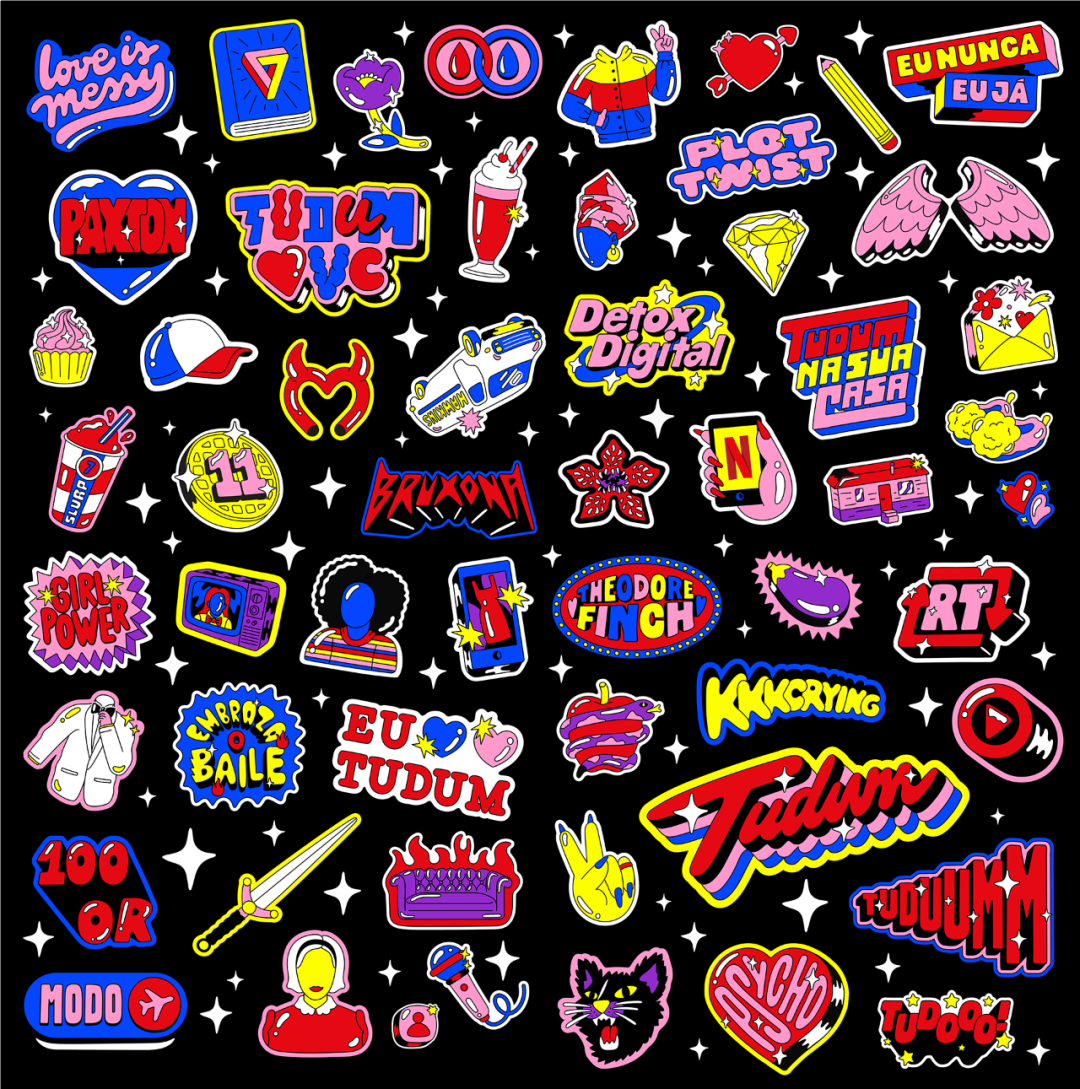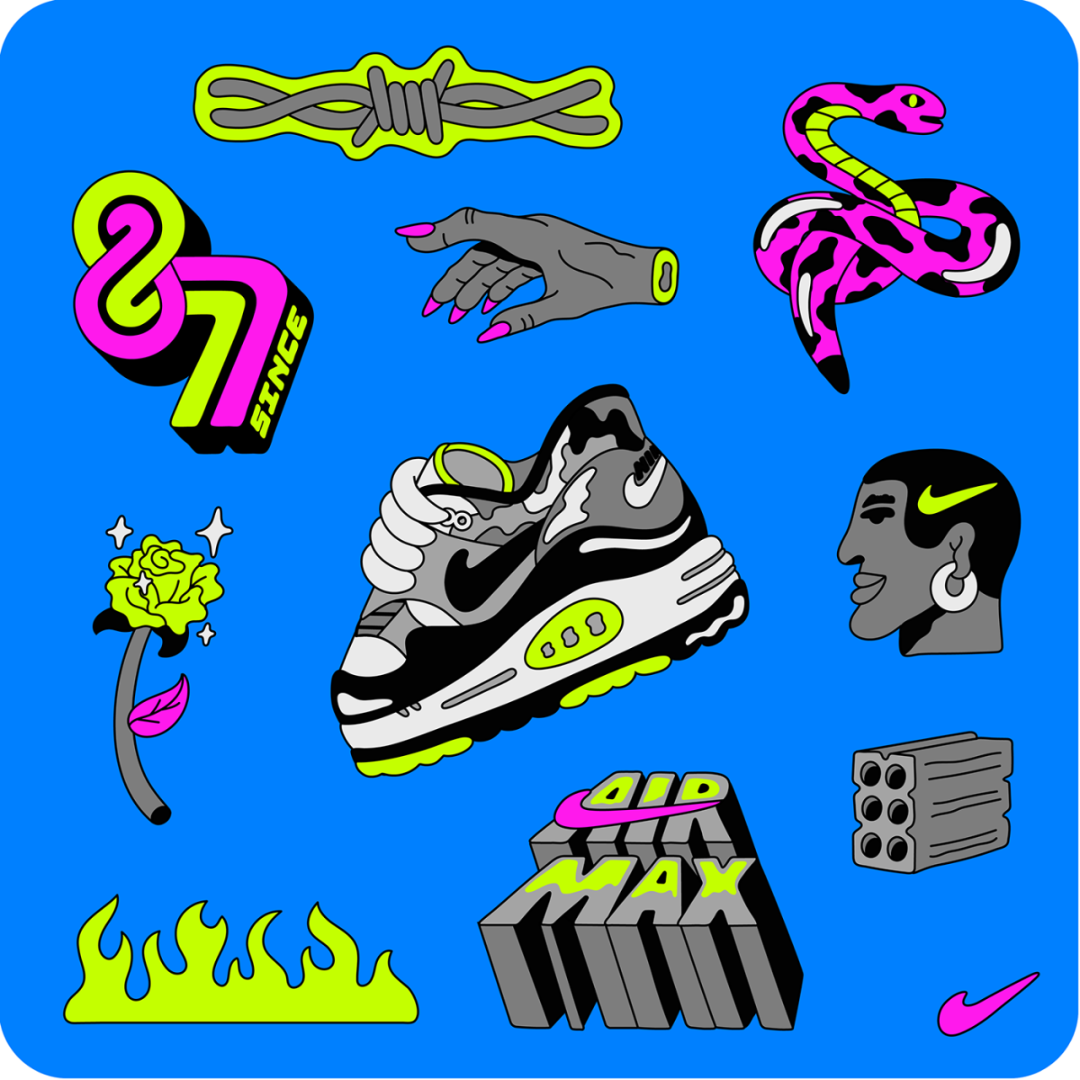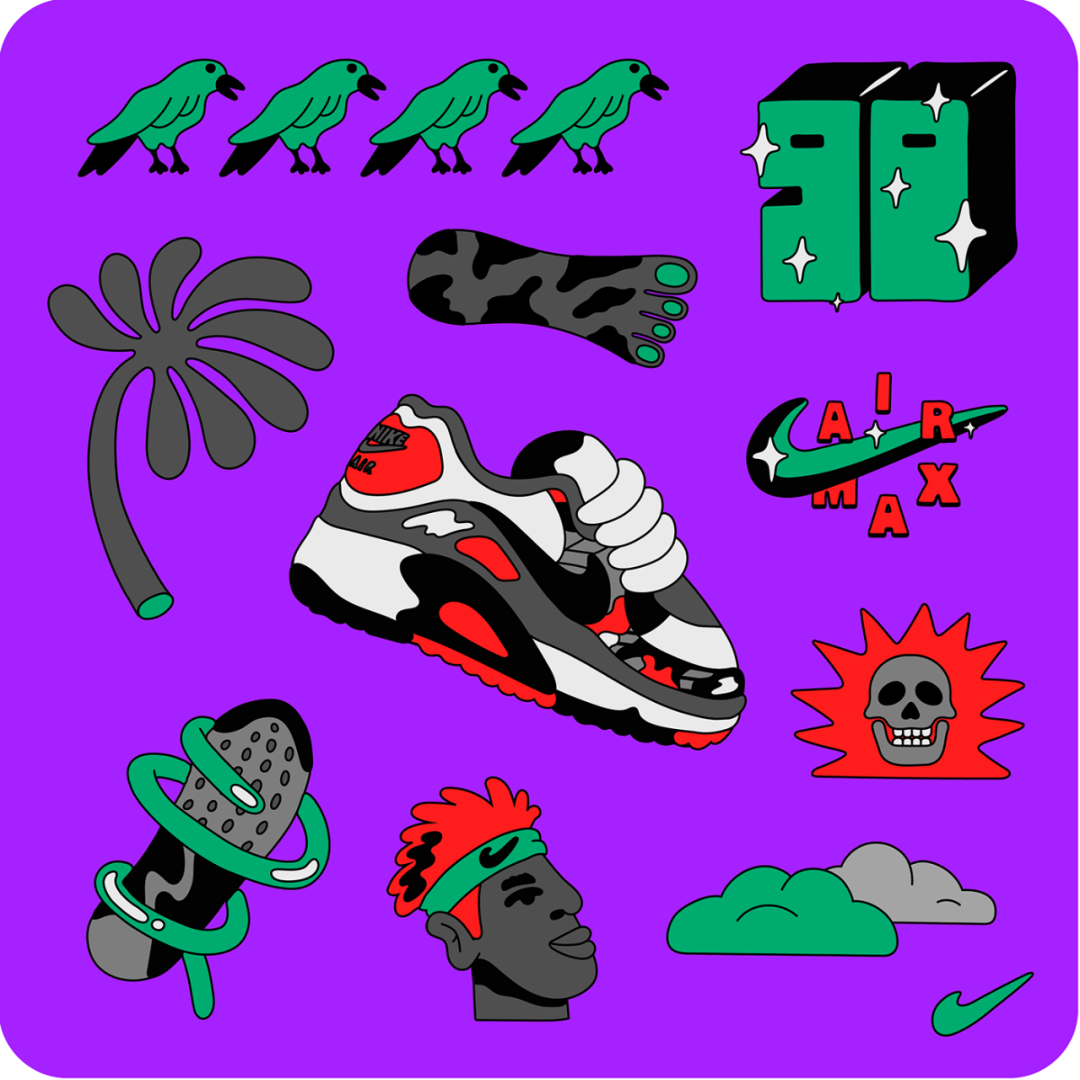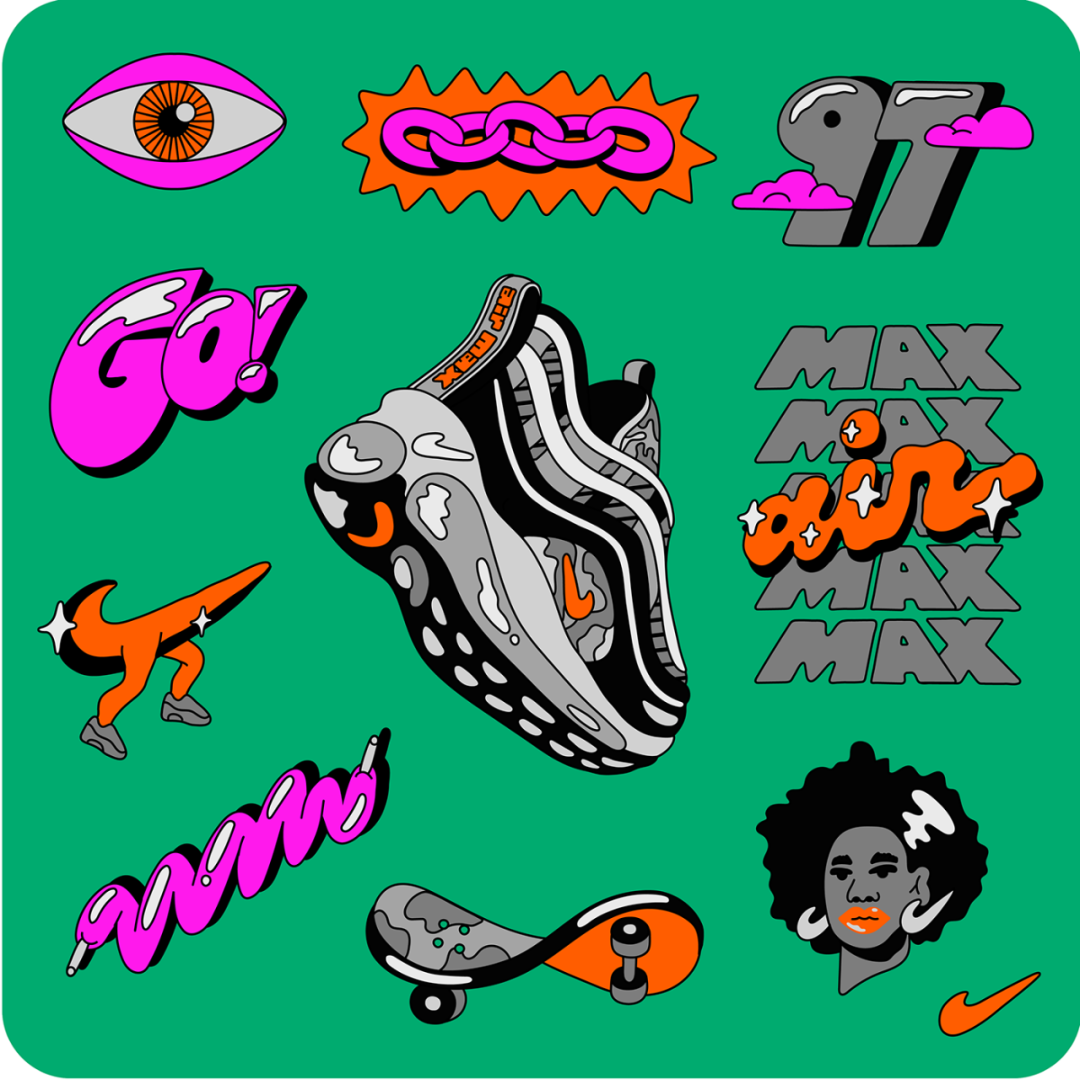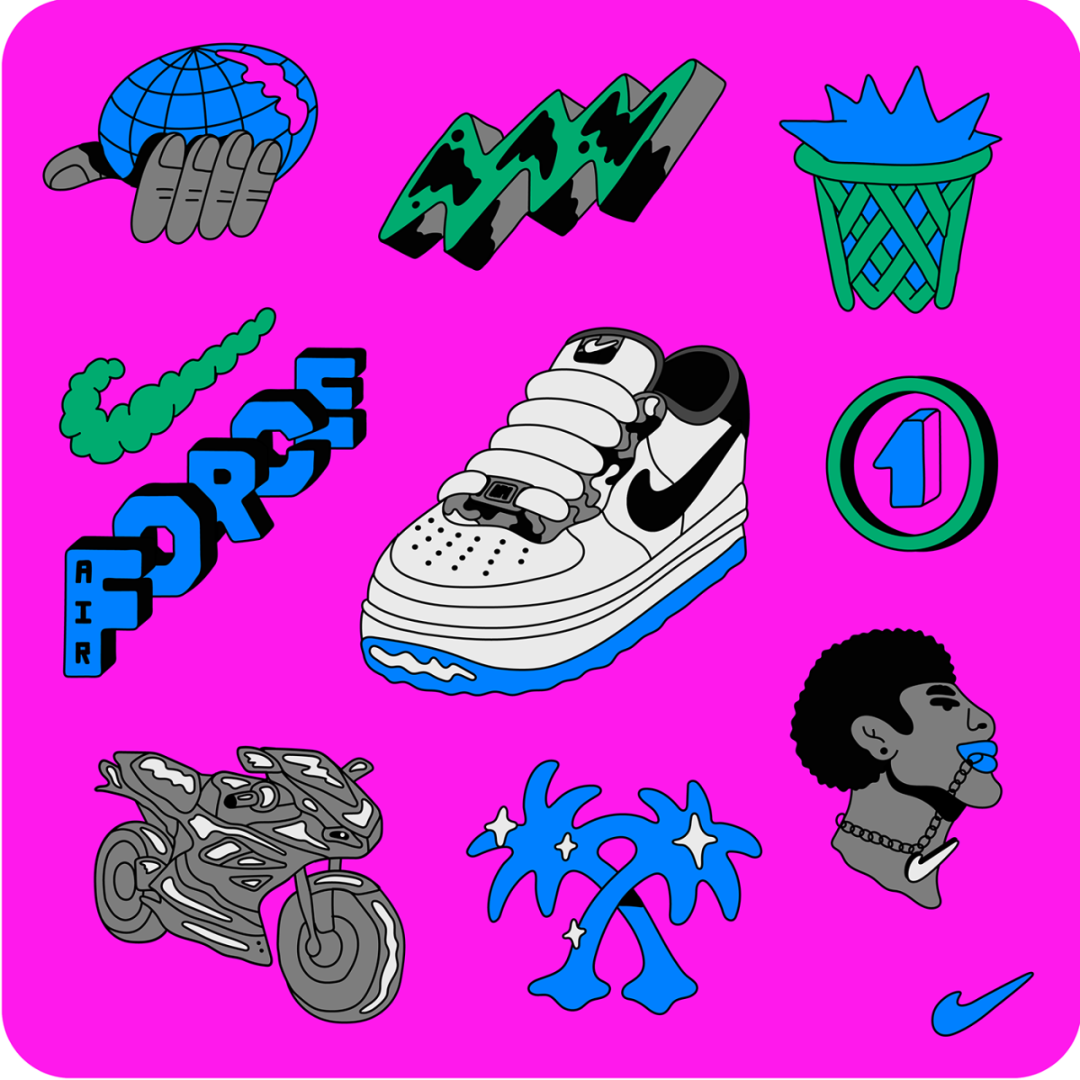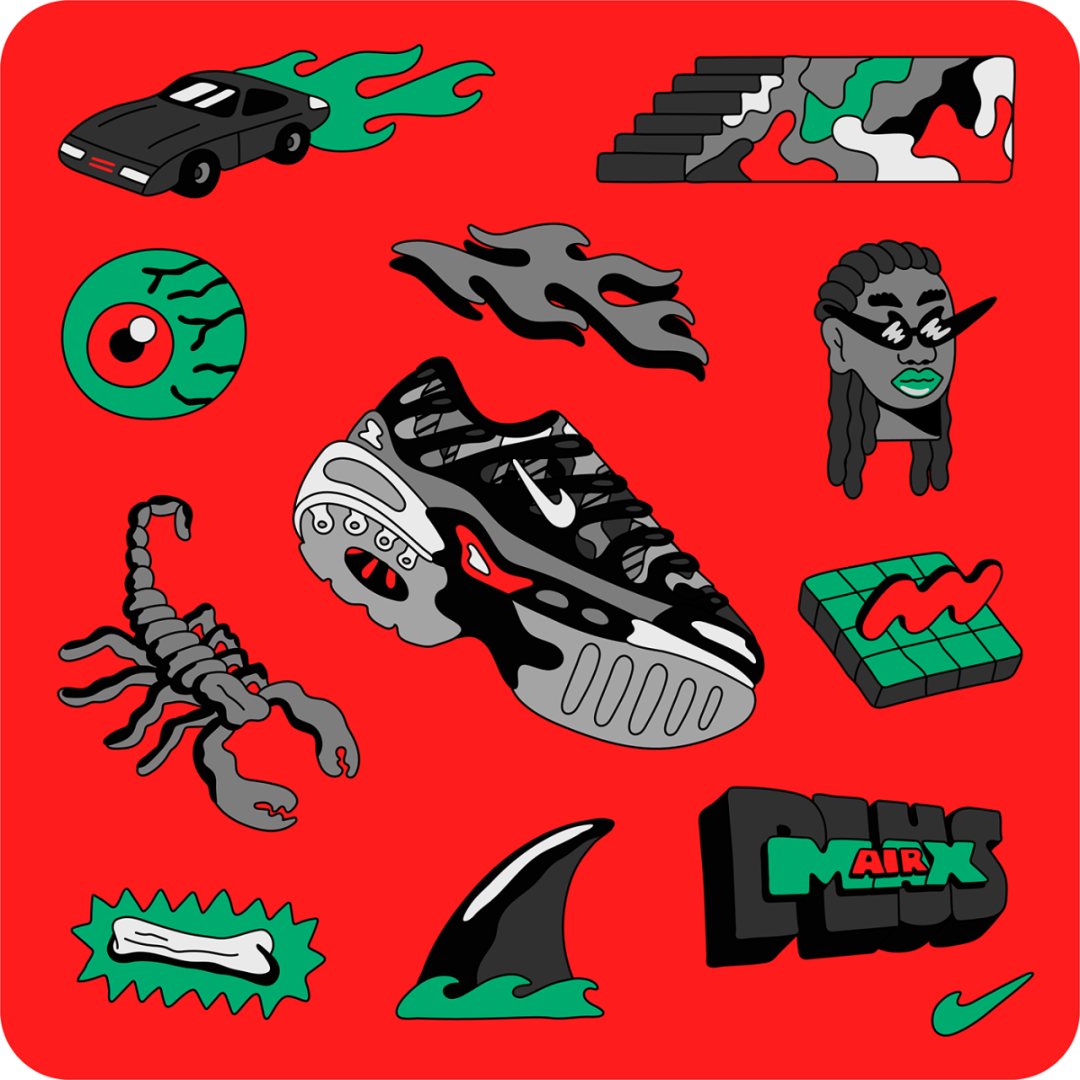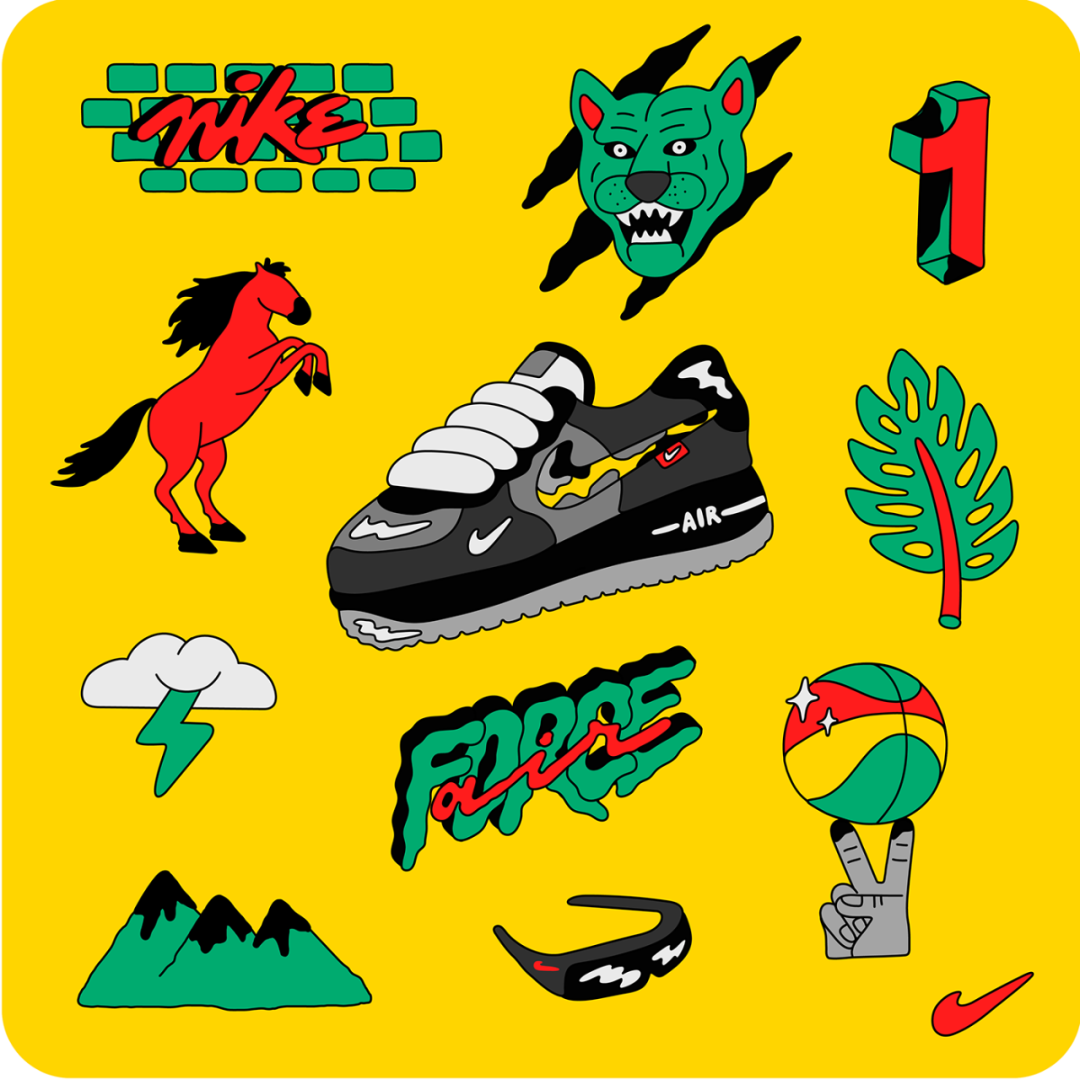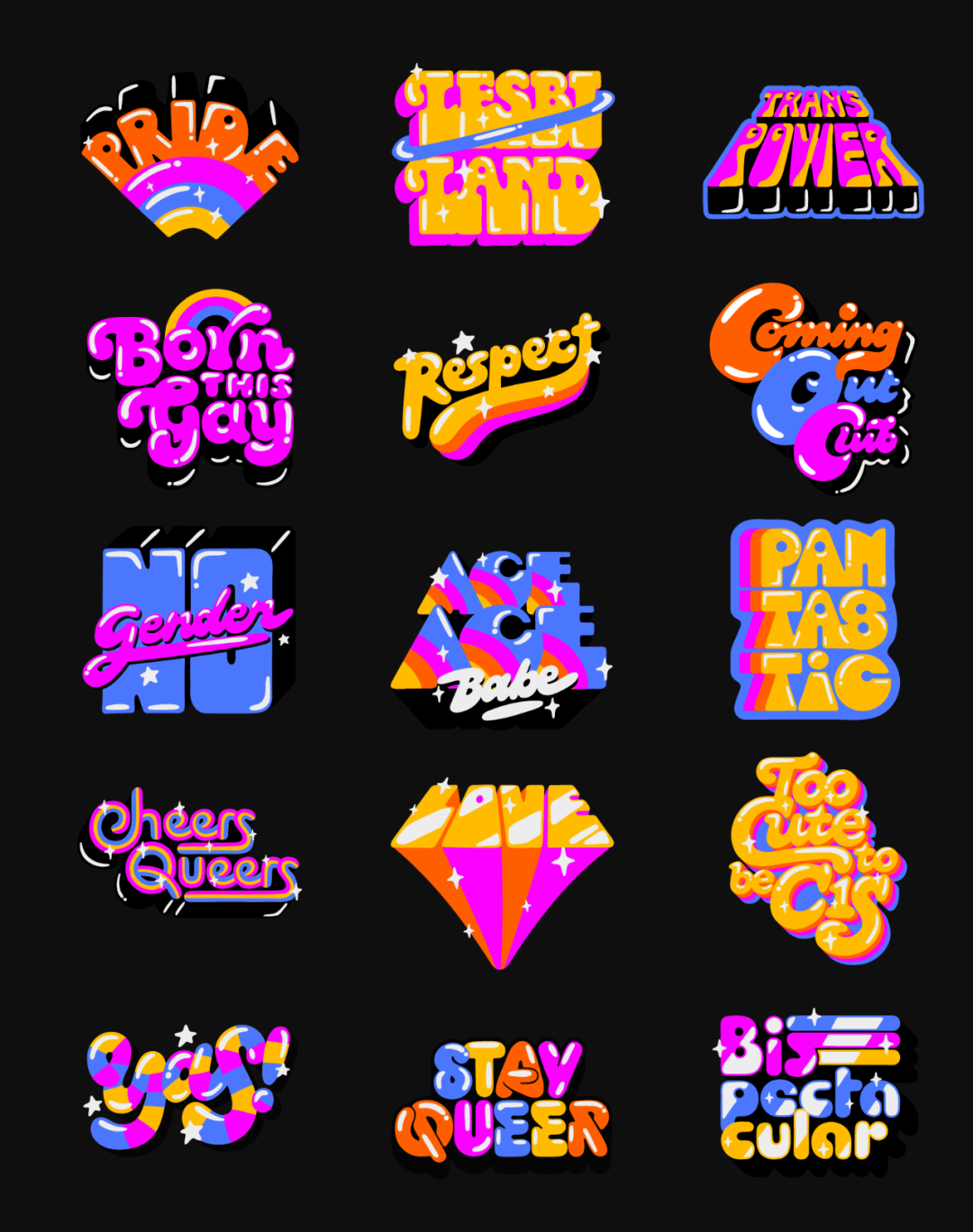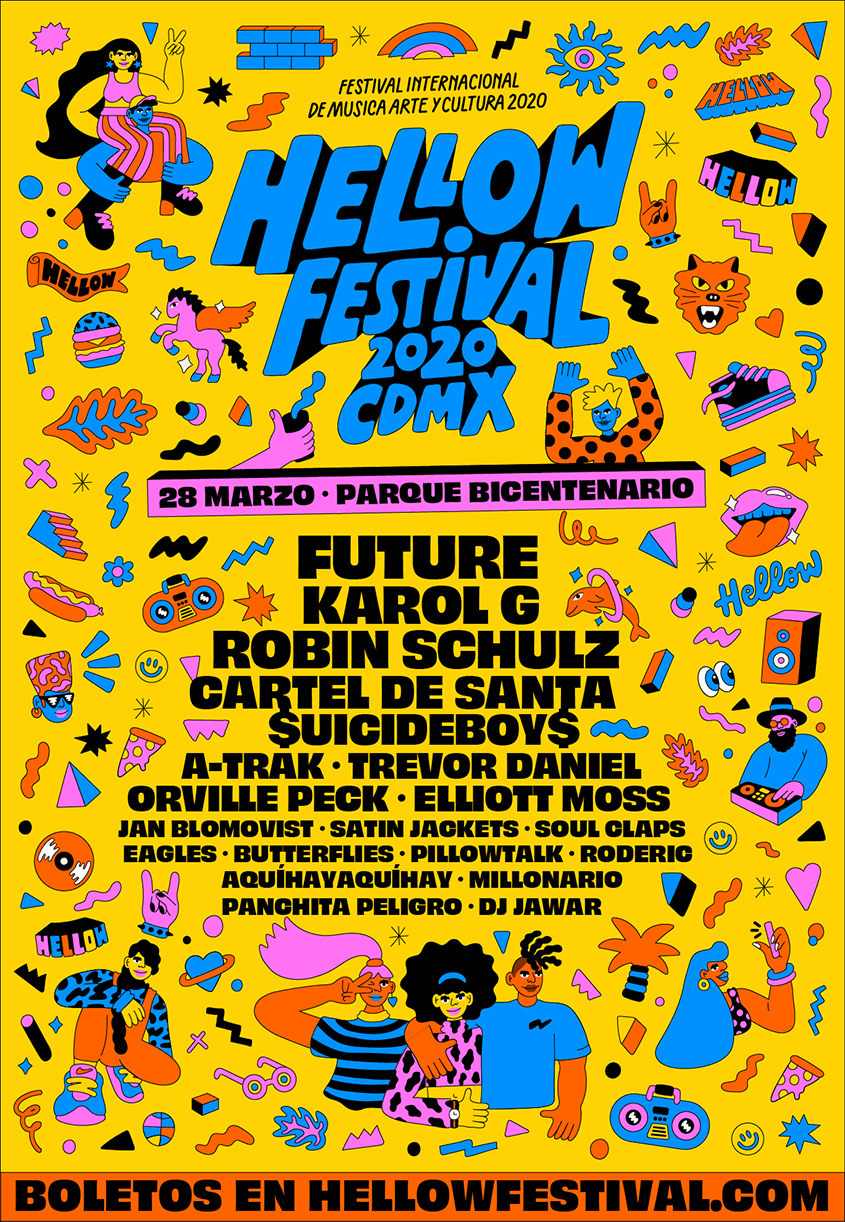
如果你喜欢潮流字体设计,一定不要错过这位巴西设计师
作为设计师
自然而然地被其主题字体和画面配色给吸引住
整个画面非常之ins风
今天的文章主题
将与潮流及夏日风格相关
Leandro Assis
是一名来自巴西的字体设计师和插画艺术家
并与众多知名互联网公司合作过
包括苹果、谷歌、迪士尼、索尼音乐、环球音乐等等
字体设计如何与插画融合一体?
如何设计一系列潮流风格的可爱字体?
潮流色彩应该如何表现?
接下来的作品也能能让你找到答案
一个星期之前他设计了
Black History Month
YouTube
作为YouTube受邀的艺术家之一
他为2021年的黑人历史月
设计制作了一个突出黑人社区创造力的Yoodle
另外一名艺术家 richard ottley 说道
当他第一次看到这个的时候
就爱上了这个插图及字体
去年12月下旬
他为 RuPaul's Drag Race Season 13
设计了一系列潮流字体
Lettering
Leandro Assis, Kate Moross,
Johnny Brennan and Anna Czuz
还有一个视频
另外
还根据字体与人物
Santiago Avila, Linus Kraemer, Margaret Bialis and George Wheeler
设计与制作了 Motion + Animation
在同一个月
还发布了为 Tudum Netflix 设计的新项目
Leandro Assis 受邀制作了100张贴纸
组成了Netflix的图腾
该项目分为两部分:
第一部分是一份100页的年鉴
里面有独家内容、游戏以及对Netflix系列和电影人才的采访
这本年鉴免费分发给20多万人
并在网上传播了数周
去年9月份
为新发布的 Nike Remix Pack
设计制作了一系列插图和文字
该项目包含了6个经典模型包装的NIKE标志性印刷品
图案、流行的颜色和材料的灵感
来自90年代的街头风格
为耐克做点什么一直是 Leandro Assis 的梦想
这个梦想终于实现了
去年6月
为 Pride Month 设计了一组 Snapchat
对于LGBTQIA + pride month
Snapchat 打电话给他
让他制作一套贴纸
表达平台对社区中人们的尊重
Leandro Assis 设计了一个未来流行的泡泡糖气氛的字型
并附上经典的排版风格和一些积极的文字信息
同年6月
为 Hellow Festival CDMX 2020 设计了新项目
Hellow音乐节是墨西哥最大的音乐节之一
在2020年,很高兴能让整个活动的品牌视觉
节日的气氛以良好的氛围为标志,
有音乐和大量的食物!
这无疑是他做过的最酷的工作之一!
除了贴纸
他在去年四月还为一个啤酒品牌设计了外包装
Boom Beer
Holvi
一家金融科技公司Holvi
为了庆祝那一年的成功和新办公室,
委托他从头开始设计一瓶啤酒
去年5月
为 Coaches Article Galileu 设计了极具特色的字体和内页
另外
他还为“BuyBlack”活动制作过字体和视频
旨在增强Facebook平台上的业务并使其更具可见性
还将字体制作成了动效
还有很多优秀的字体设计和插画项目
就不在这一一分享
夸张有趣的字体设计
丰富的色彩搭配
有趣的插图
这些都是 Leandro Assis 的风格
夏天即将来临
相信大家都会用到这类的设计
希望今天的分享能给大家带来灵感